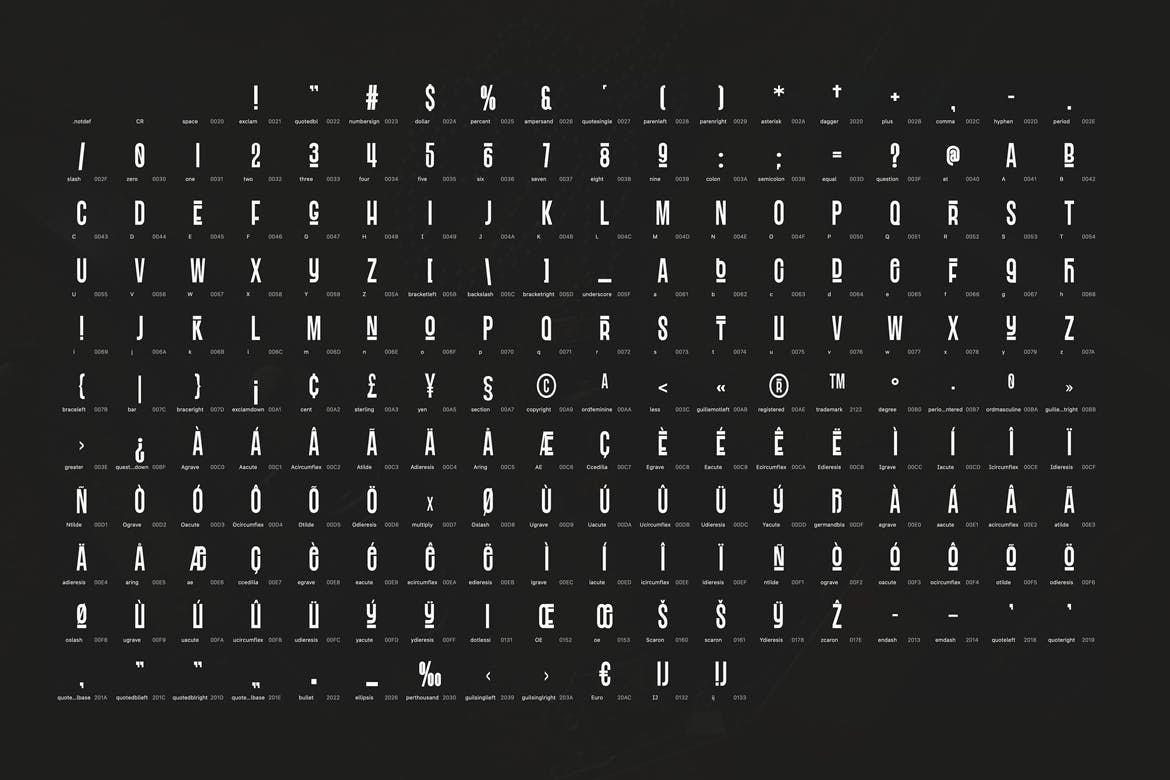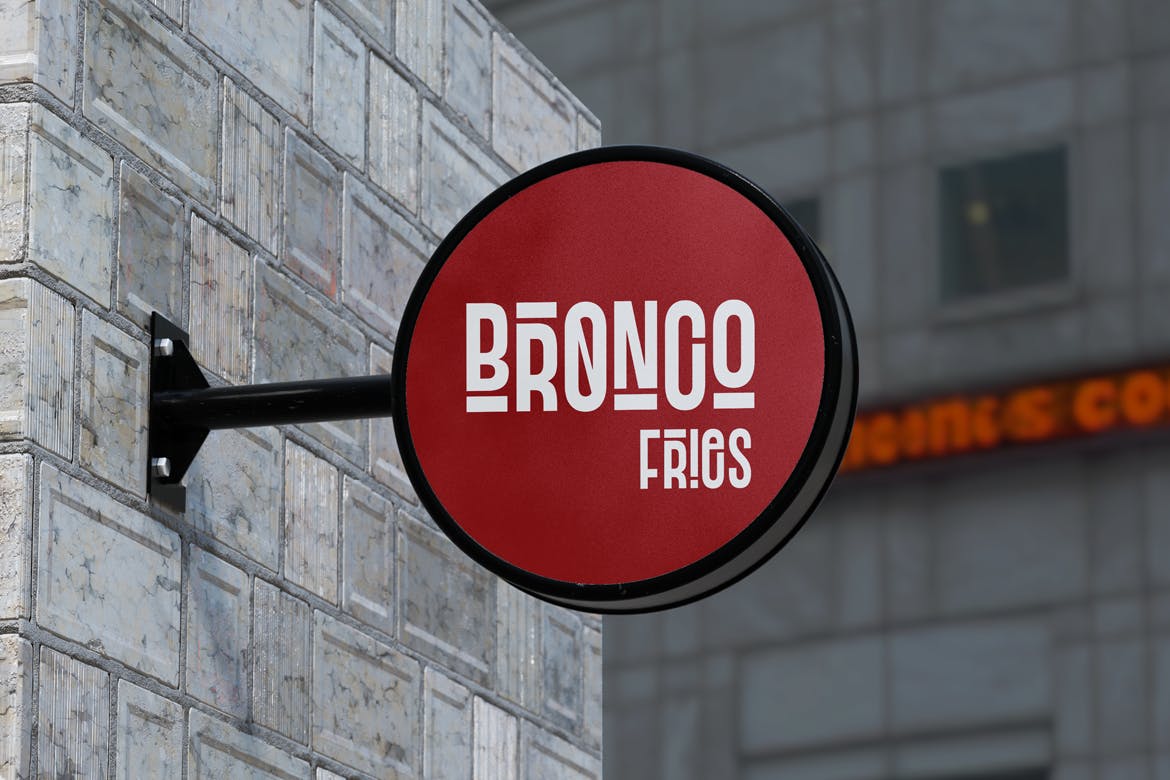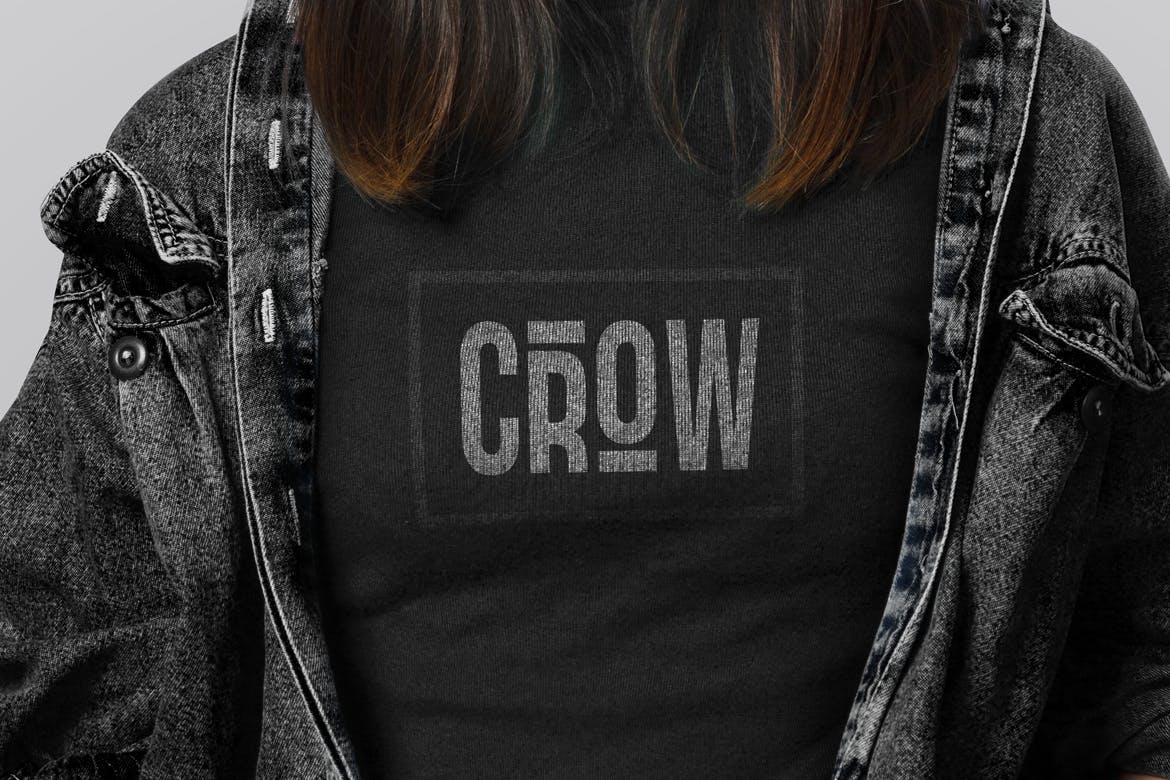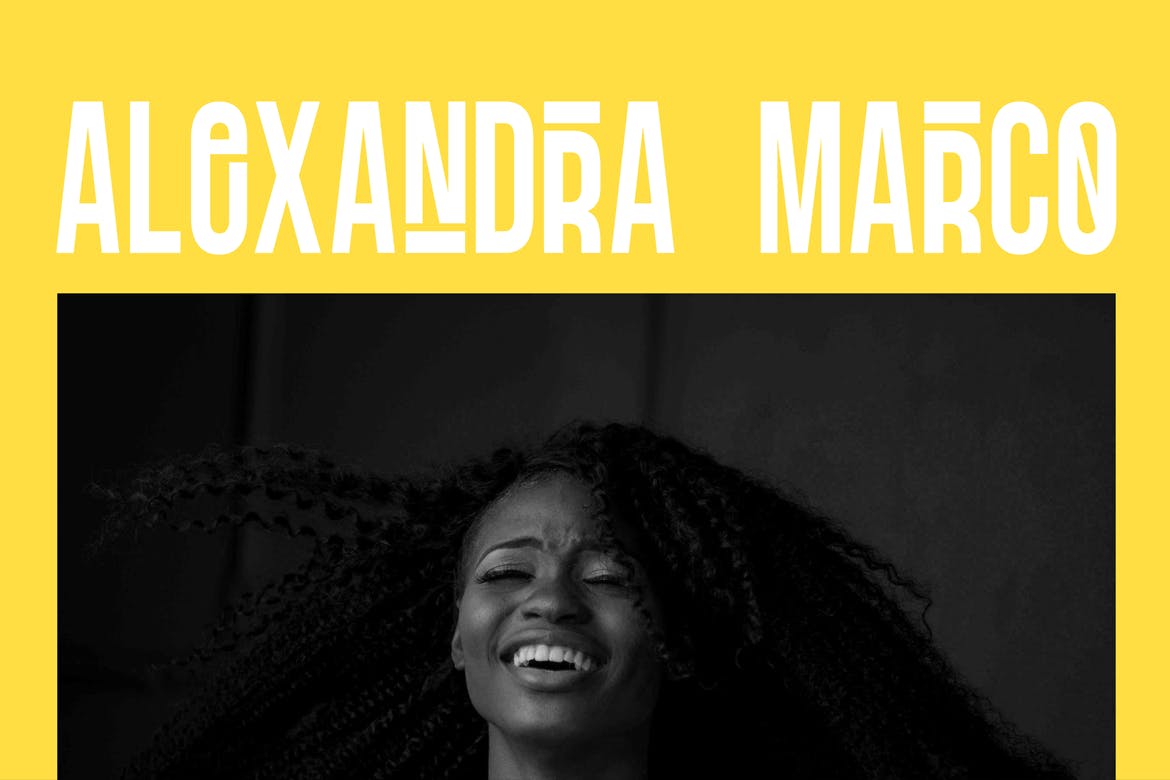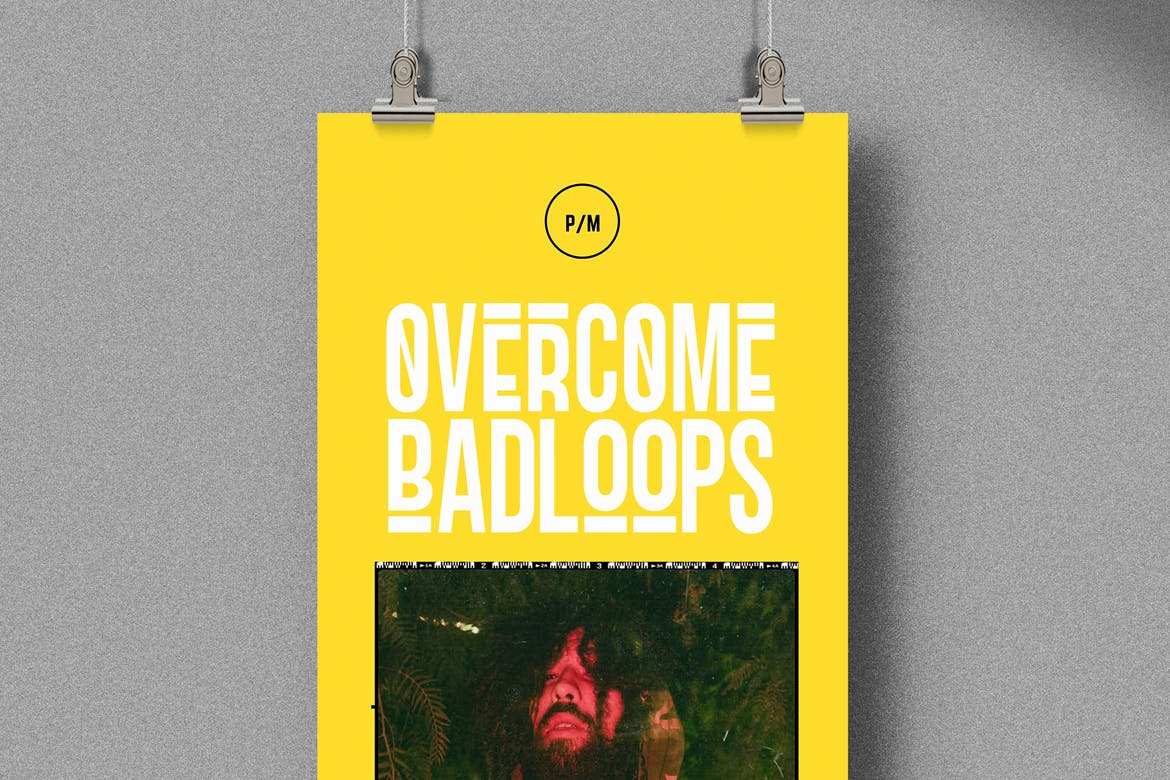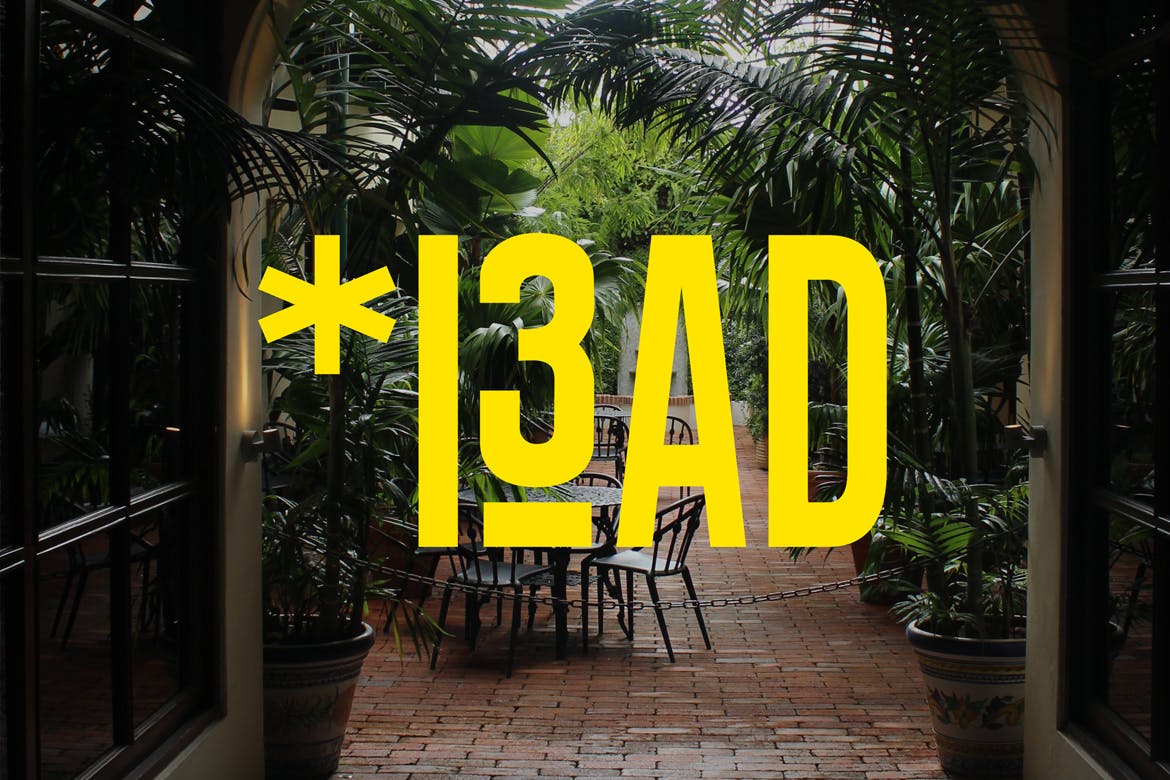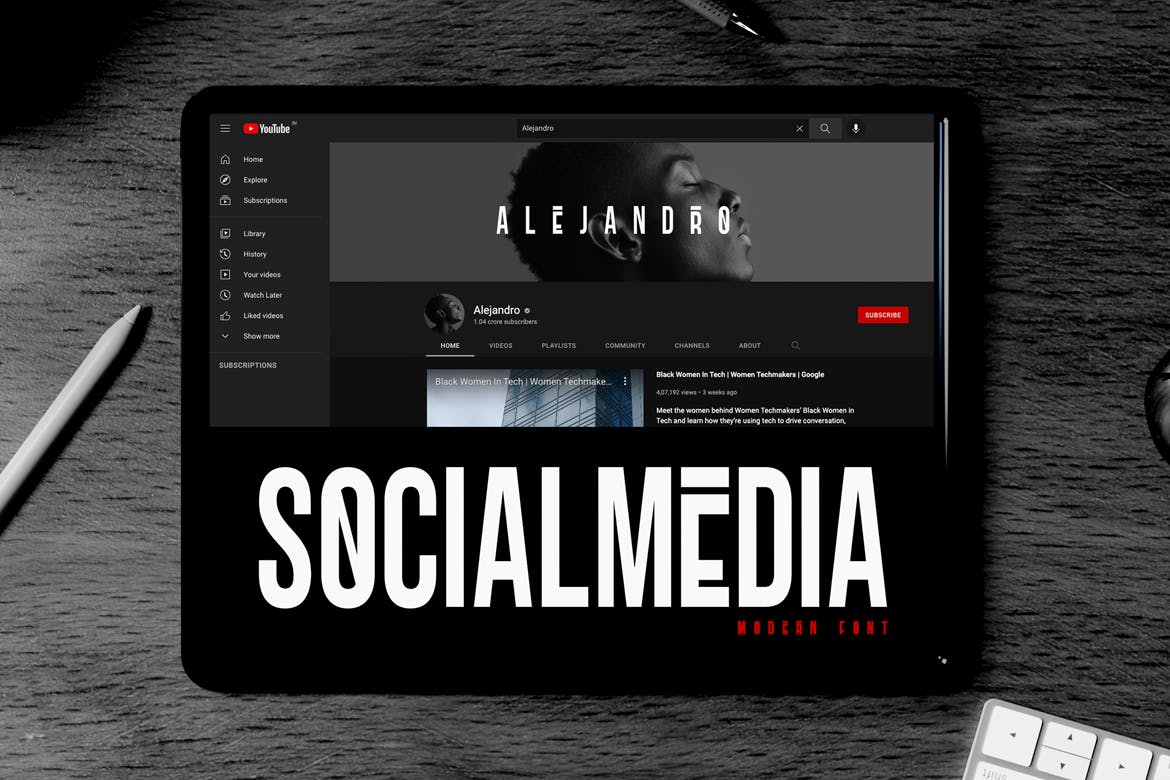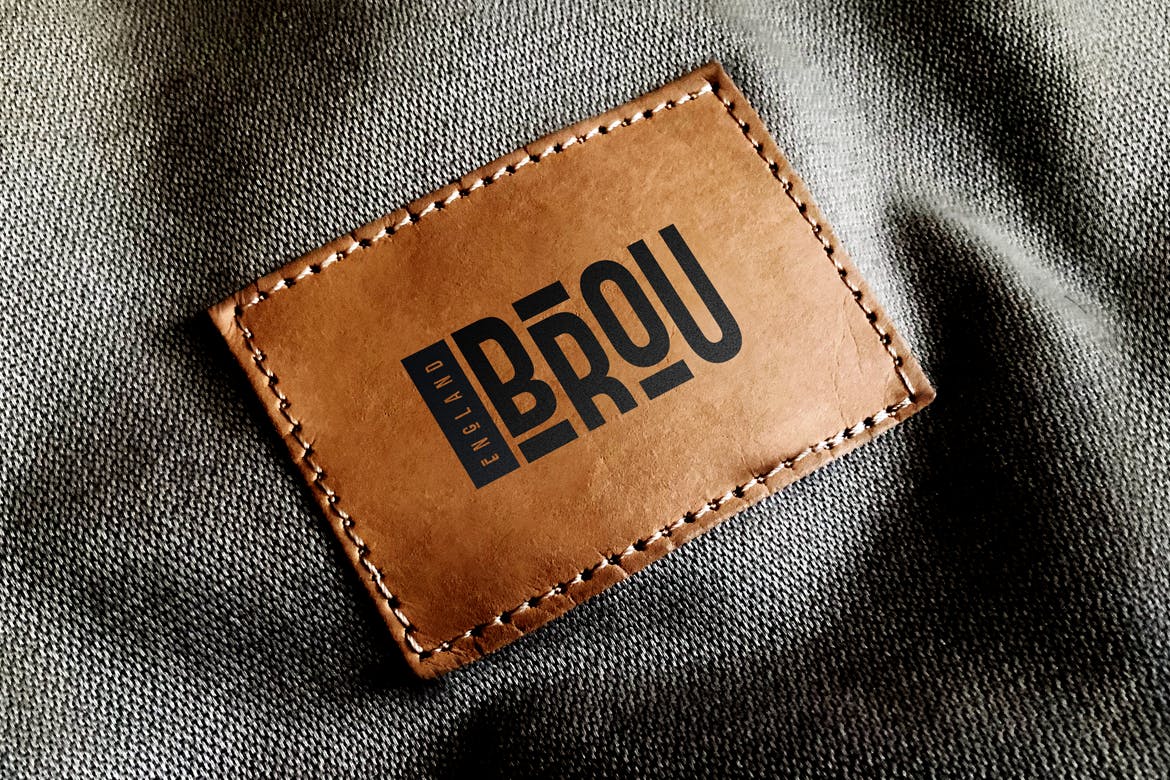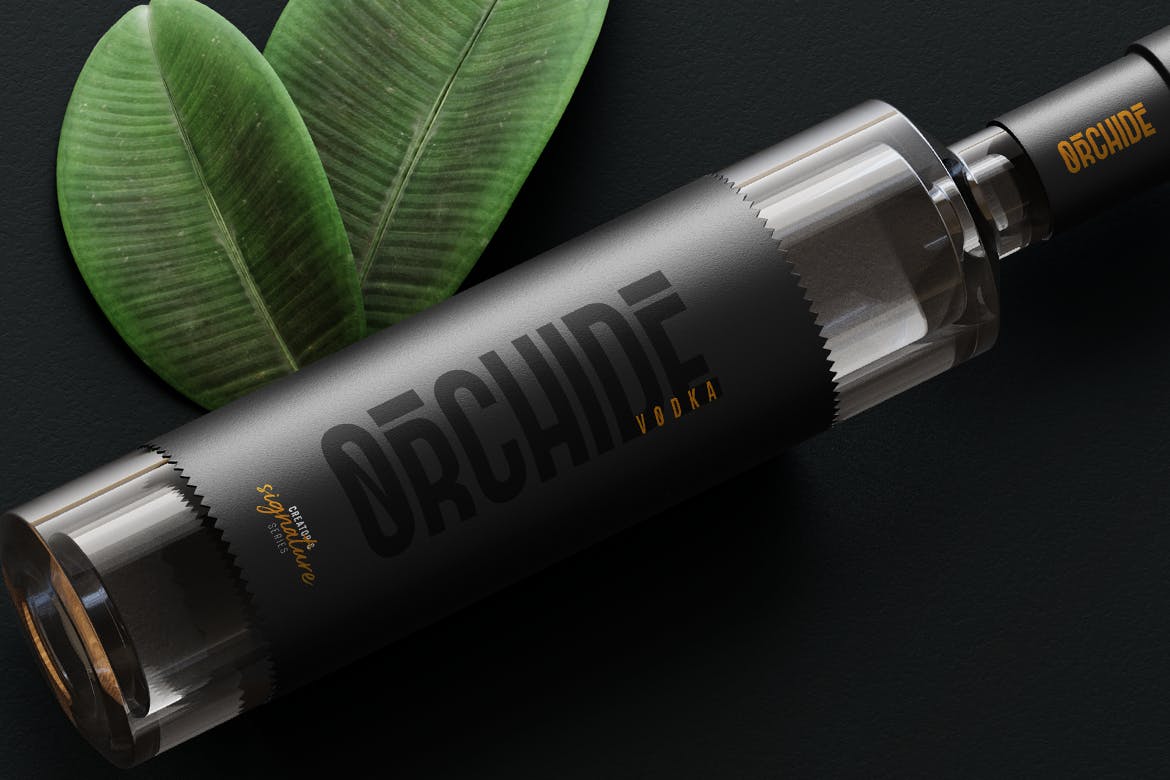
Blandit - فونت لوگو مدرن
فونت بلاندیت یک خانواده فونت نمایشی است که برای طراحی لوگوهای مینیمالیستی مناسب میباشد. این فونتها برای ایجاد نامنویسها، عناوین، شعارها، پوسترهای فیلم، سرخطها، حروف بزرگ، زیرنویسها، طراحیهای لوگو و بنرهای بزرگ بسیار مناسب هستند. طراحیهای کلاسیک و تزئینی با تایپوگرافی وب نیز امکانپذیر است.